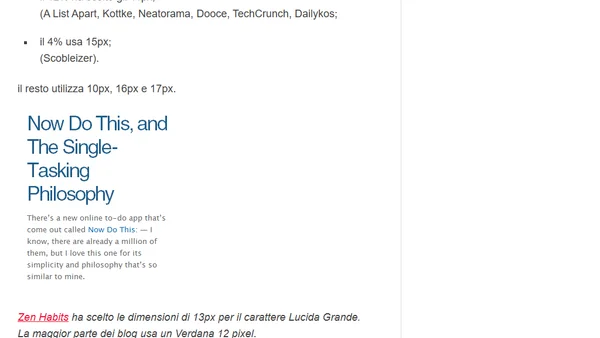
Che tipografia utilizzano i top blogger? (parte 3)
Read OriginalTerza parte di uno studio sul design dei blog più popolari secondo Technorati. L'articolo presenta dati statistici sui font (Verdana, Lucida Grande, Arial, Georgia) e sulle dimensioni in pixel (12px, 13px, 14px) più utilizzate per il corpo del testo, offrendo consigli pratici per un bilanciamento ottimale tra leggibilità e layout.